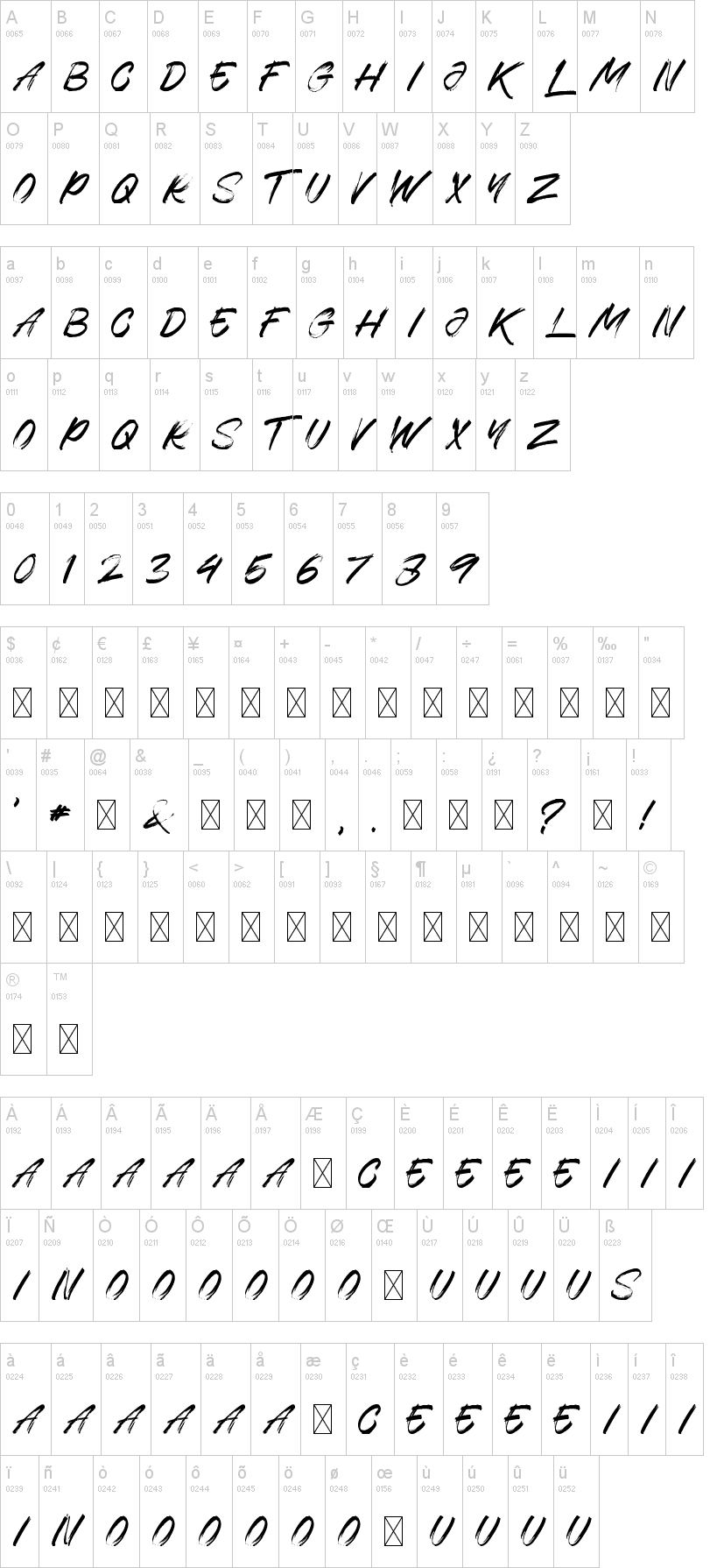
Rhogsainel 是一款简洁、现代的英文字体,由著名的设计师Rhoda Wai 创作。它的特点是简练的笔画,清晰的字形,以及柔和的曲线。字体采用了细节丰富的设计,使其具有较强的视觉冲击力,可以支持多种文字样式和大小,适用于各种场景。内容介绍
Rhogsainel是一款非常不错的手写艺术字体,具有很好的视觉感,适合于文化类的宣传设计、商业类品牌的广告和产品包装设计以及个性化文字排版等较多场景。